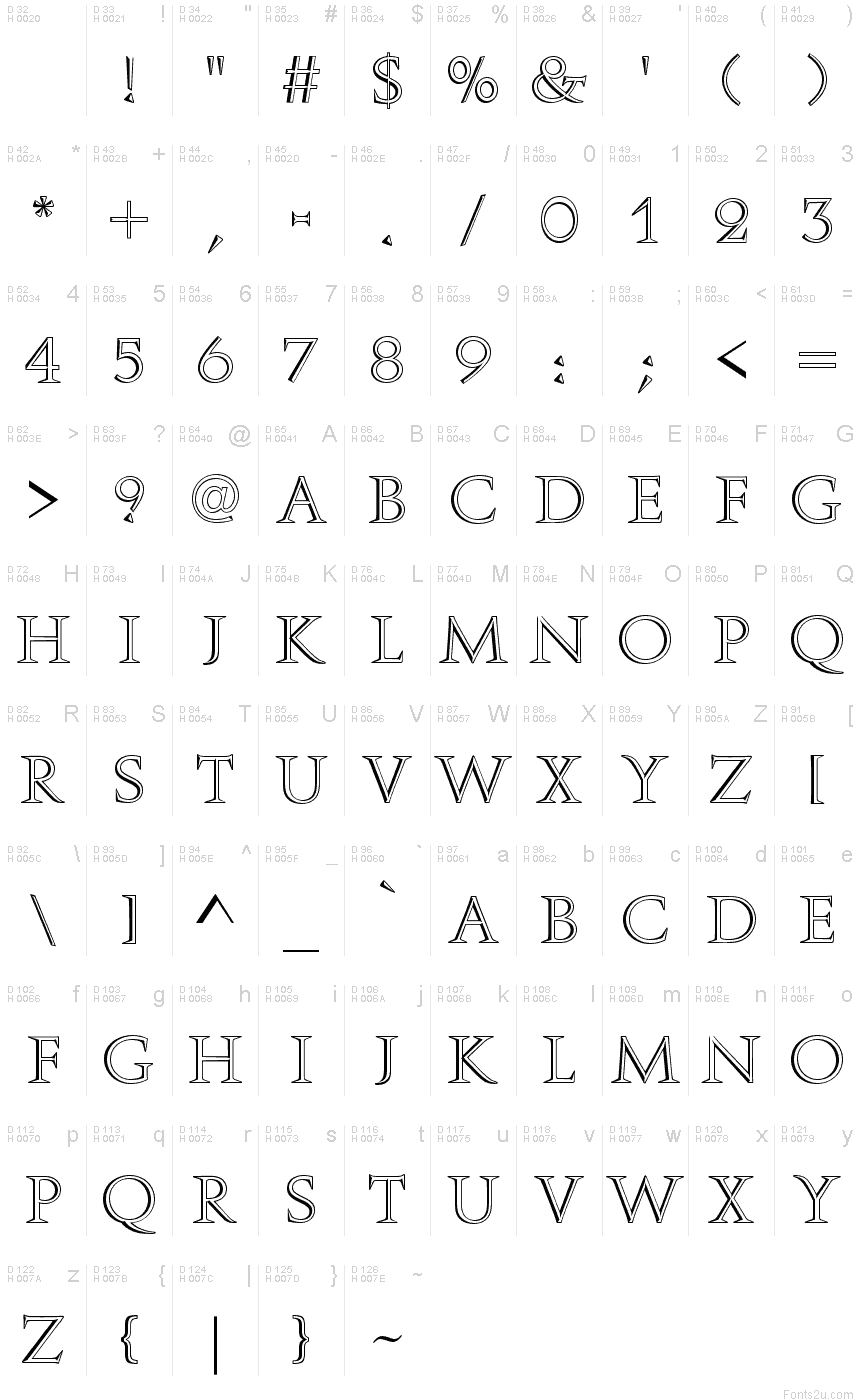
Caesar Open od Digital Typeface Corp. to bezpłatny, obrysowany krój szeryfowy, który łączy rzeźbioną elegancję rzymskich inskrypcji z lekkim, eterycznym sznytem. Wysokie, dostojne litery są wykończone czystymi konturami, dzięki czemu ich wnętrza pozostają otwarte, a kolor tła staje się częścią projektu. Rezultat jest monumentalny i zarazem wyrafinowany – niczym kamienny relief przeniesiony na papier w formie delikatnych linii – co nadaje tytułom charakteru bez zbędnego wizualnego ciężaru.
Dzięki Caesar Open zyskujesz majestatyczny, historyczny wyraz, który świetnie sprawdza się w nowoczesnych projektach. Ten bezpłatny krój pisma doskonale prezentuje się na okładkach książek, plakatach muzealnych, etykietach win, zaproszeniach ślubnych i w menu restauracji, które wymagają klasycznego akcentu. Świetnie sprawdzi się również w logotypach i nagłówkach redakcyjnych, gdzie potrzebujesz powagi bez wizualnej masywności. Połącz Caesar Open z prostym, humanistycznym krojem bezszeryfowym w tekście głównym i pozwól tym wyrzeźbionym konturom grać główną rolę w Twojej typografii.